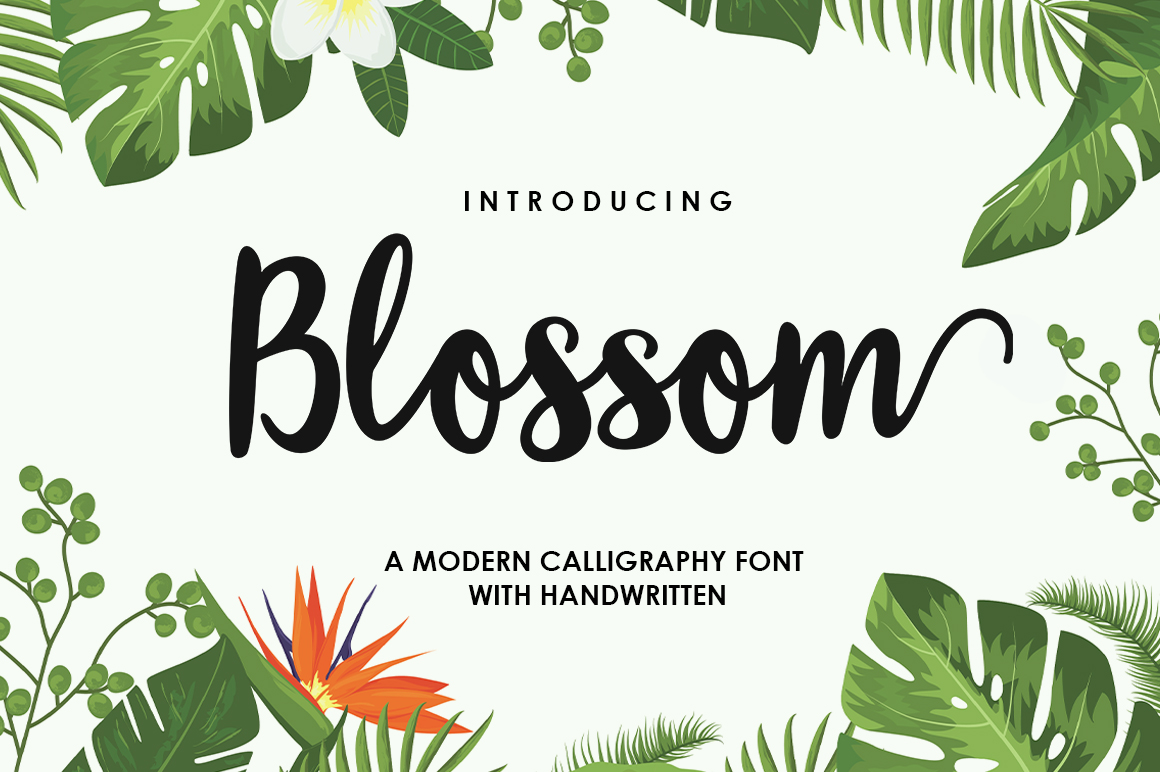
Blossom Script Font
Encontrar los elementos de diseño adecuados puede ser un desafío, pero Blossom Script Font ofrece una colección excepcional que eleva tu trabajo al instante.
Ya sea que estés creando productos POD (impresión bajo demanda), invitaciones de boda o gráficos para redes sociales, Blossom Script Font es una opción ideal.